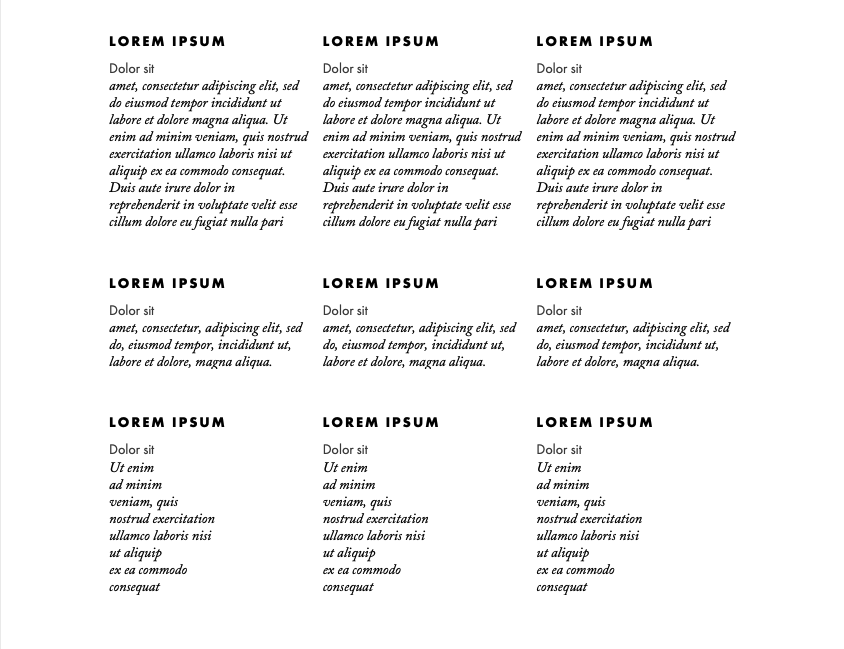
Kursivschrift für ganze Abschnitte (Fließtexte oder Aufzählungen)
kurze Frage: ist es typografisch korrekt, ganze Abschnitte in Kursivschrift zu setzen?
Hintergrund: ich habe eine große Überschrift, darunter eine Zwischenüberschrift (kleiner) und danach folgt dann die eigentliche Information. Durch die Kursivschrift möchte ich eine visuelle Hierarchie erreichen und fördern.
Beispiel:
Überschrift
Zwischenüberschrift 1
item 1, item 2, item 3, ...
Zwischenüberschrift 2
item 1, item 2, item 3, ...
Wie verhält es sich, wenn die Items oben Fließtext wären?
Die Frage zielt nicht auf Ästhetik ab, sondern lediglich auf typografische Korrektheit.
Phillip
Meine Frage wäre: Wenn sich der Fließtext bereits durch andere Merkmale von den Überschriften in Kapitälchen, Fettung, Größe etc. absetzt,wieso muss er dann noch einmal extra ausgezeichnet werden. Oder stehen dem dann Textteile, die recte gesetzt sind, gegenüber? Sonst nämlich kann und sollte man sich die Kursivierung sparen.
Gute Frage, jedoch klar mit ja zu beantworten, d.h. die Unterscheidung zw. Zwischenüberschrift und Fließtext ist sonst schwach; es wirkt alles zu ähnlich, während durch das Setzen in kursiv die Elemente klar unterscheidbar werden und der Text (Auflistung durch Kommata getrennt) nicht zuletzt auch viel dynamischer aussieht (einen Screenshot darf ich aus rechtlichen Gründen leider nicht anhängen).
P.S. Kapitälchen gibt es keine, ich habe nur die Möglichkeiten hier genutzt, um den Sachverhalt darzustellen.
Wenn es hilft: Überschrift und Zwischenüberschrift in Futura PT, Auflistung in Caslon kursiv.
Hallo @phillip2300, prinzipiell kannst du typografisch korrekt ganze Abschnitte kursiv setzen (siehe z. B. Willberg/Forssmann, »Lesetypografie« [2010], S. 140). Die kursive Schrift an sich ist ja ursprünglich sogar zu diesem Zweck entwickelt worden.
Doch wie so oft gilt: es kommt drauf an. Hier hängt die Entscheidung für oder gegen kursivierte Abschnitte wesentlich davon ab, ob der verwendete Kursivschnitt selbst auch fließtexttauglich ist. Verschrägte Grotesken oder allzu expressive Antiqua-Varianten etwa machen das Lesen ganzer Abschnitte schwieriger. Andere (auch zeitgenössische) Schriften warten mit sorgfältig gearbeiteten Kursivschnitten auf, die in auch in großen Mengen noch gut lesbar sind.
Edit: deine zwischenzeitliche Antwort sehe ich gerade erst. Kannst du deine Inhalte vielleicht durch Blindtext ersetzen, um ein Bild des tatsächlichen Satzes hochladen zu können?
Klar - hier ein Beispiel:
- Fließtext
- Auflistung, Komma-getrennt
- Auflistung, zeilenweise
kann man so machen. ist aber seeehr ungewöhnlich. (und auch ein bissl mühsam fürs auge)
generell muss (meinem gefühl nach) der kursive textanteil immer in der minderheit sein gegenüber dem sonstigen text.
kursiv ist die ausnahme (auszeichnung), gerade ist der normalfall.
Wie wäre es, die Zwischenüberschriften zu kursivieren und den Fließtext recte zu setzen? Bringt das optisch nicht genug Unterscheidung?
Und um was für eine Textsorte handelt es sich? Worum geht es? Wer sind die potentiellen Leser?
Wie wäre es, die Zwischenüberschriften zu kursivieren und den Fließtext recte zu setzen?
Wollte ich auch vorschlagen und würde ich so umsetzen.
kann man so machen. ist aber seeehr ungewöhnlich.
Das wollte ich hören und fasse es als Ermutigung auf ;-)
Wie wäre es, die Zwischenüberschriften zu kursivieren und den Fließtext recte zu setzen? Bringt das optisch nicht genug Unterscheidung?
Ja, ist aber langweilig :-) Wie eben Carlito geantwortet, "darf" es durchaus etwas ungewöhnlich sein - so lange erlaubt.
Ich versuche den vorgeschlagenen Weg trotzdem. Danke!
Und um was für eine Textsorte handelt es sich? Worum geht es? Wer sind die potentiellen Leser?
Es geht um eine Auflistung von Dienstleistungen/Leistungsportfolio. Leser sind keine Typografie-Experten, aber Digitalspezialisten, die - so glaube ich - auch mal etwas ausser der Reihe "vertragen".
Das wollte ich hören und fasse es als Ermutigung auf ;-)
Wenn ich ausbrechen wöllte, würde ich – abgesehen von anderen Gestaltungselementen – erstmal bei der Schriftwahl beginnen:
Auflistung in Caslon kursiv
Die wird anstrengend. Die schmale Laufweite und geringe x-Höhe erschweren das Erfassen der Zeichen. Und dann schau mal wie, beispielsweise im Vergleich zur hier verwendeten kursiven Tisa, die Punzen optisch zulaufen. Das würde ich mir als Leser nicht lang antun.
Intuitiv würde ich immer noch dagegen votieren, mehr als nötig zu kursivieren und dies somit als Auszeichnung zu verwenden, in dem von Dir gezeigten Beispiel funktioniert es aber tatsächlich, ist durch die klare Aufteilung noch gut erfassbar und sieht an auch ganz gut aus.